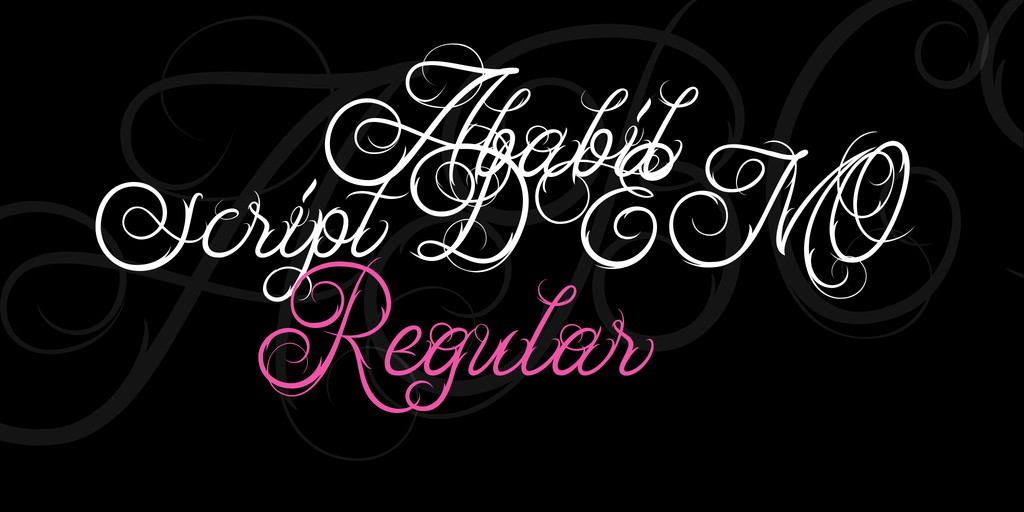
Ababil Script Font
A Ababil Script Font é uma elegante escolha para qualquer projeto que exija um toque romântico e antiquado no design. Inspirada no estilo blackletter, a fonte tem seus traços densos e arranjos arquitetônicos que remetem à era da Gutenberg. Ideal para texturas históricas ou editoriais de literatura clássica, esta escolha de fontes é perfeita para aqueles projetos que desejam um toque especial ao adicionar um pouco do passado no design atual. Hamilton, o designer desta fonte, trouxe à vida esse estilo arcaico com precisão e cuidadosa atenção aos detalhes. As linhas finas da Ababil Script fornecem uma ótima base para qualquer tipo de texto, enquanto os traços mais grossos trazem um toque elegante que dá ao design um charme único e singular. Ideal tanto para aplicativos digitais quanto para impressões profissionais, a fonte se encaixa perfeitamente em uma variedade de ambientes. Com suas características distintas desta categoria do blackletter, a Ababil Script oferece uma experiência visual única que combina a modernidade com um toque nostálgico. É uma escolha ideal para aqueles projetos que desejam um toque inovador na hora de colocar as letras em seu lugar. Há espaço e liberdade para a criatividade, garantindo que qualquer projeto esteja sempre impecavelmente representado.